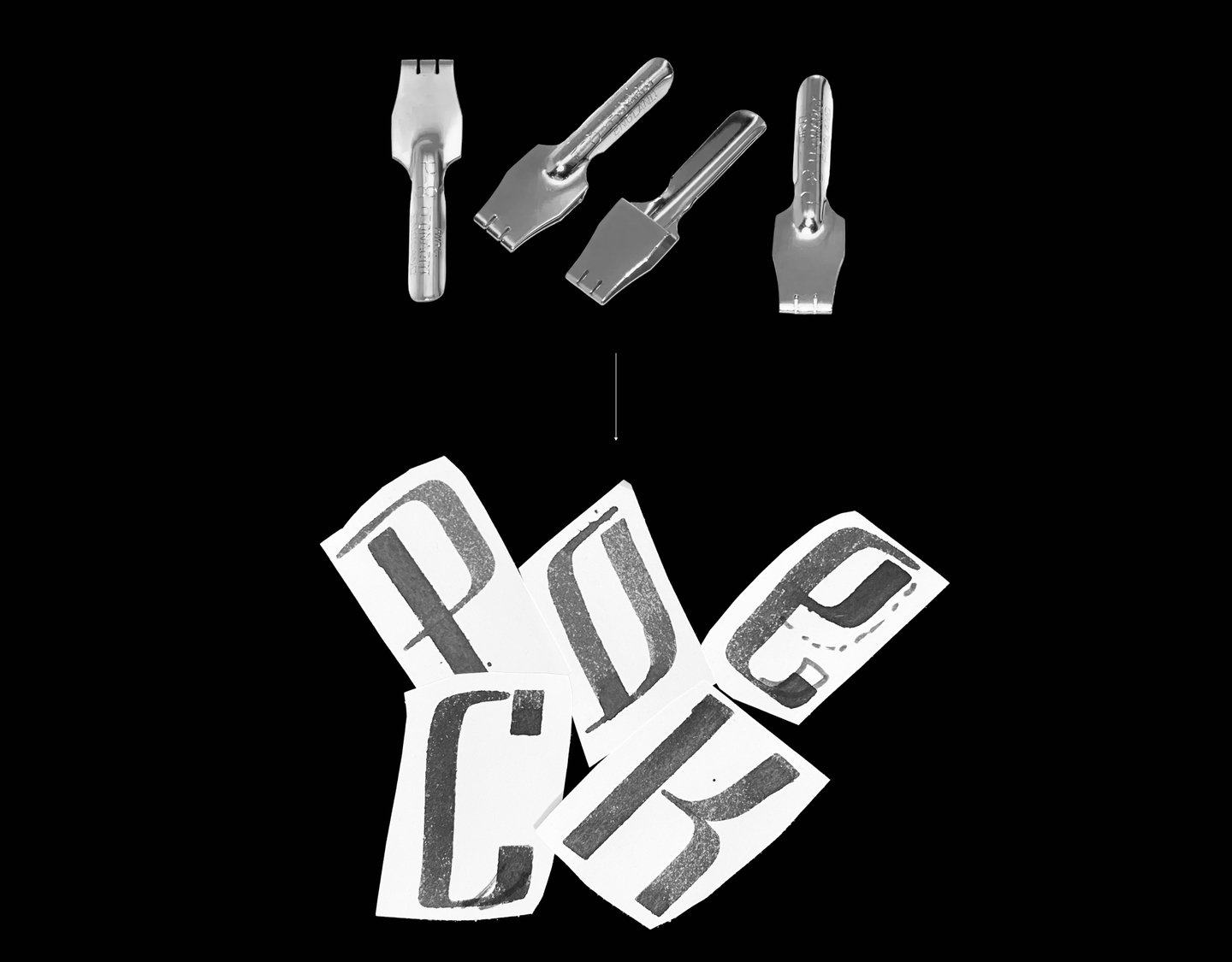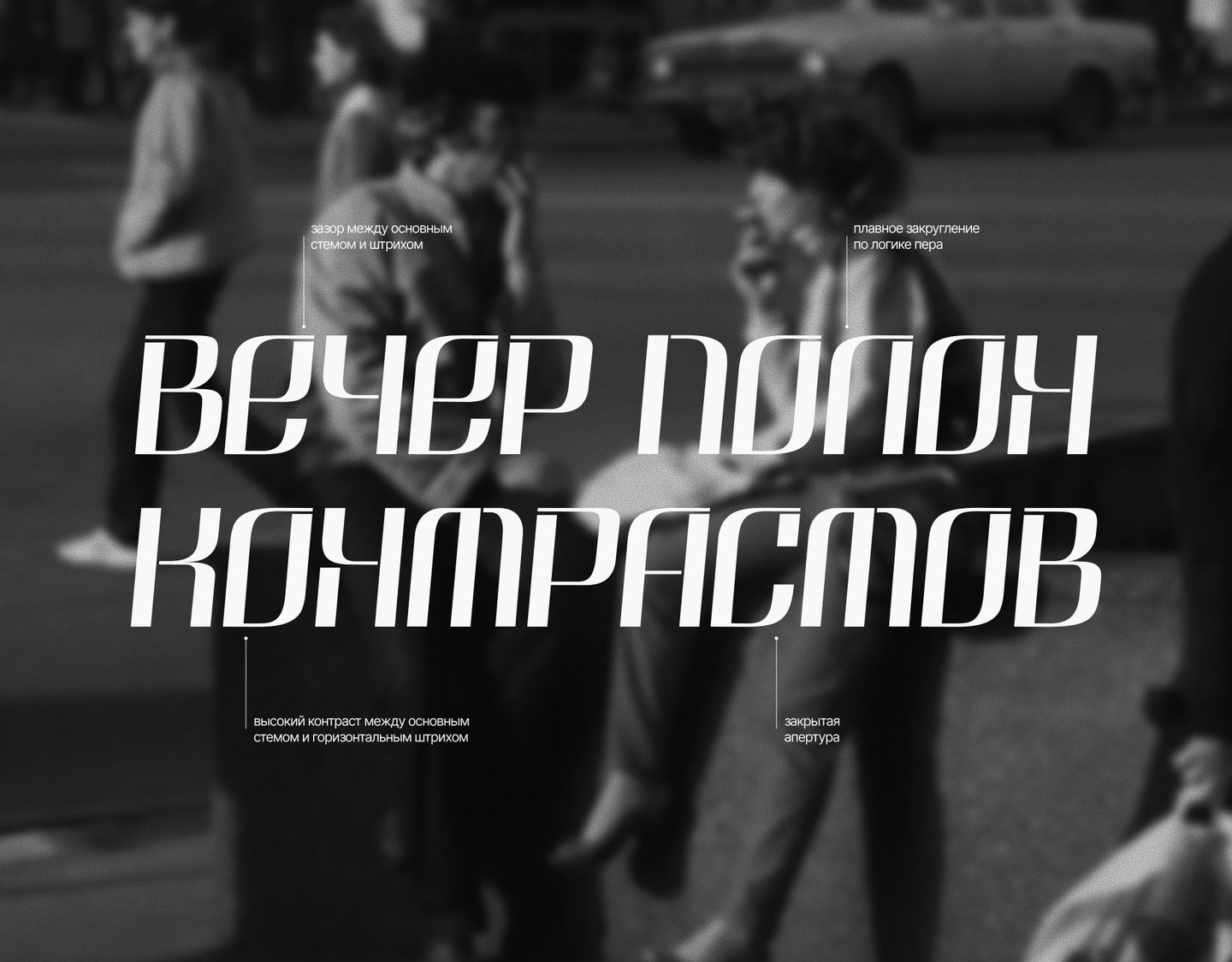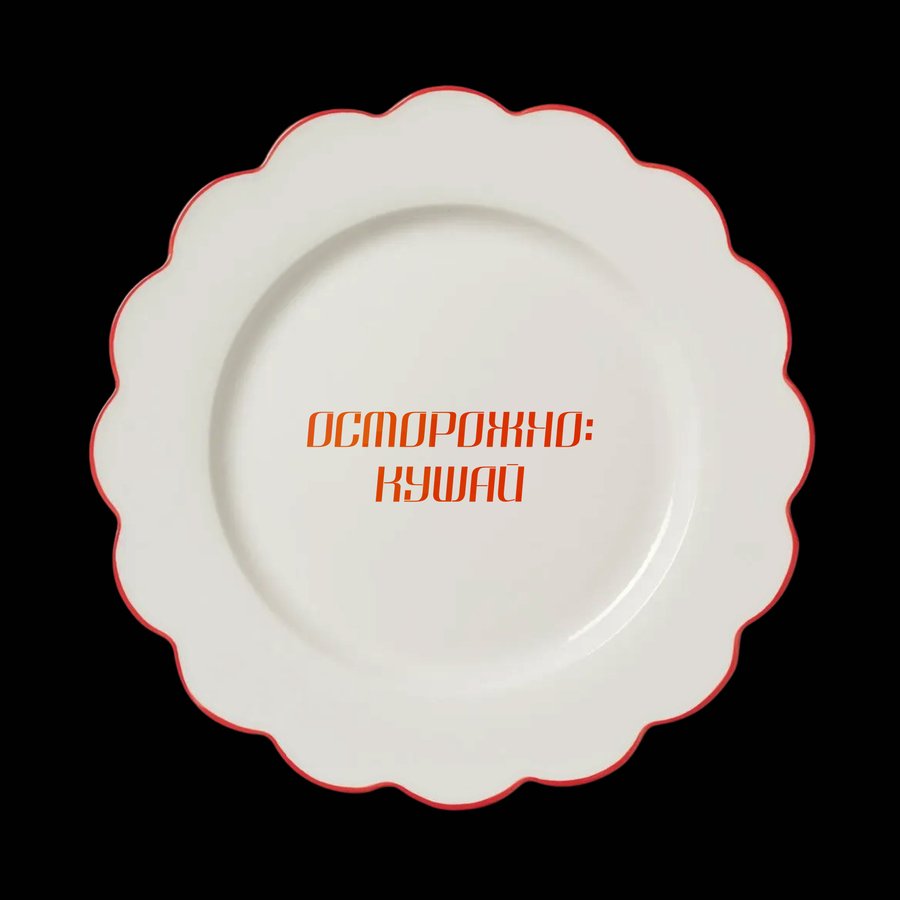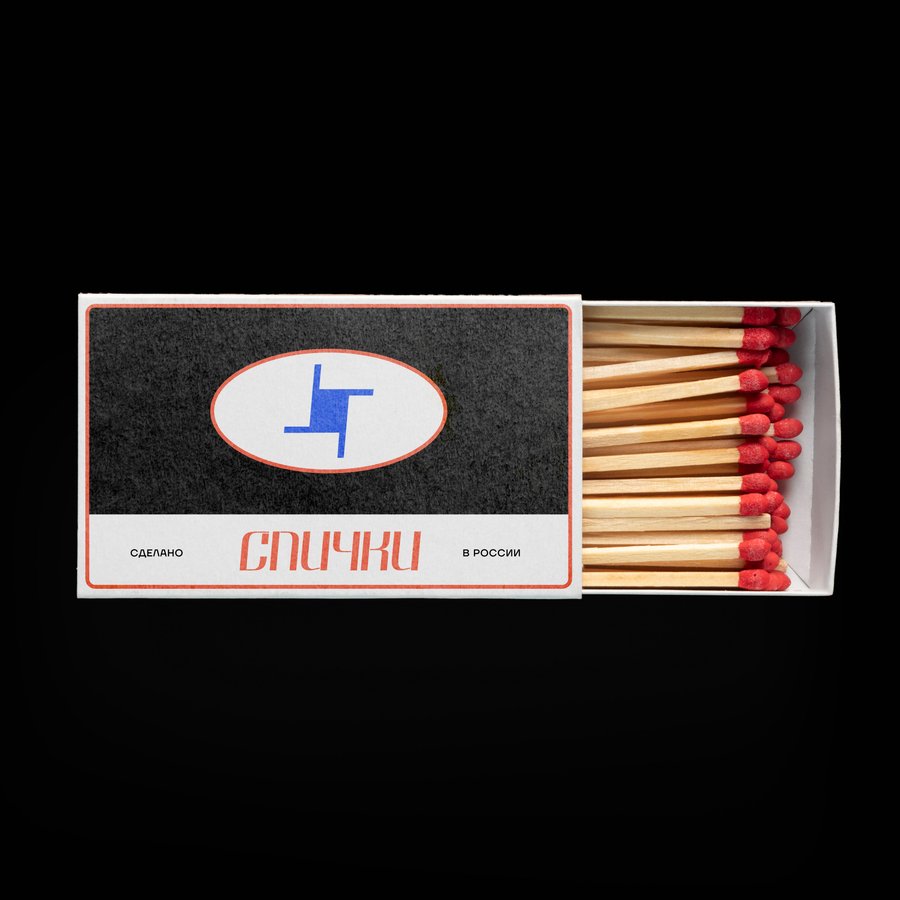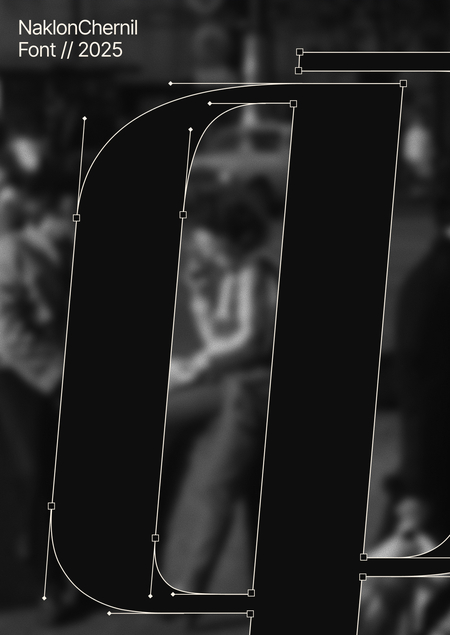
NaklonChernil Font
Графика шрифта NaklonChernil вырастает из инструмента своего создания — плакатного пера. Его форма напрямую фиксирует жест руки и угол письма, превращая процесс в основу визуального языка.